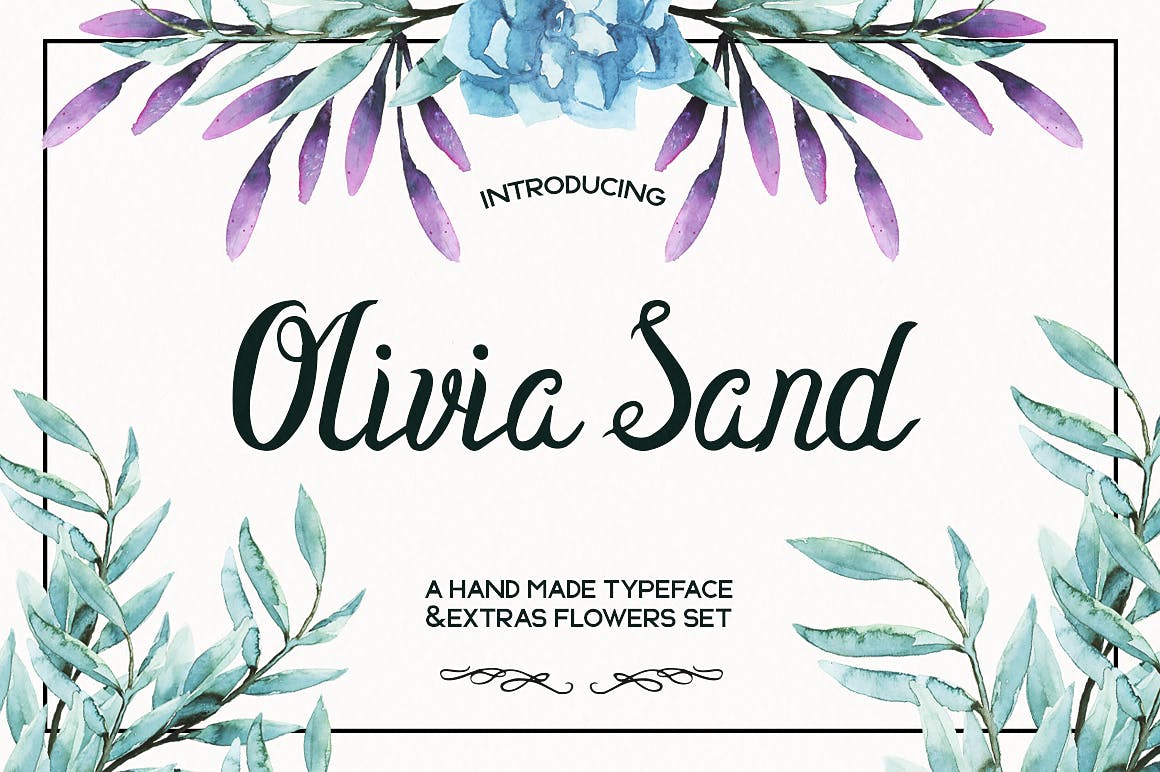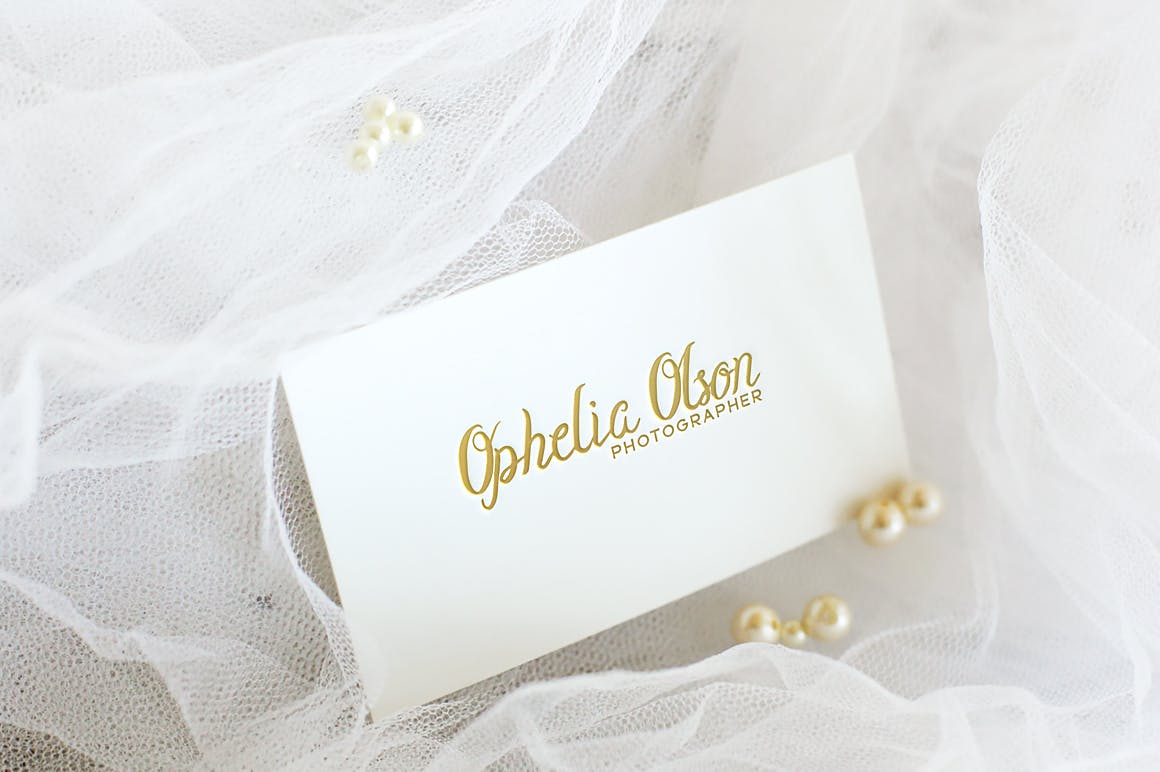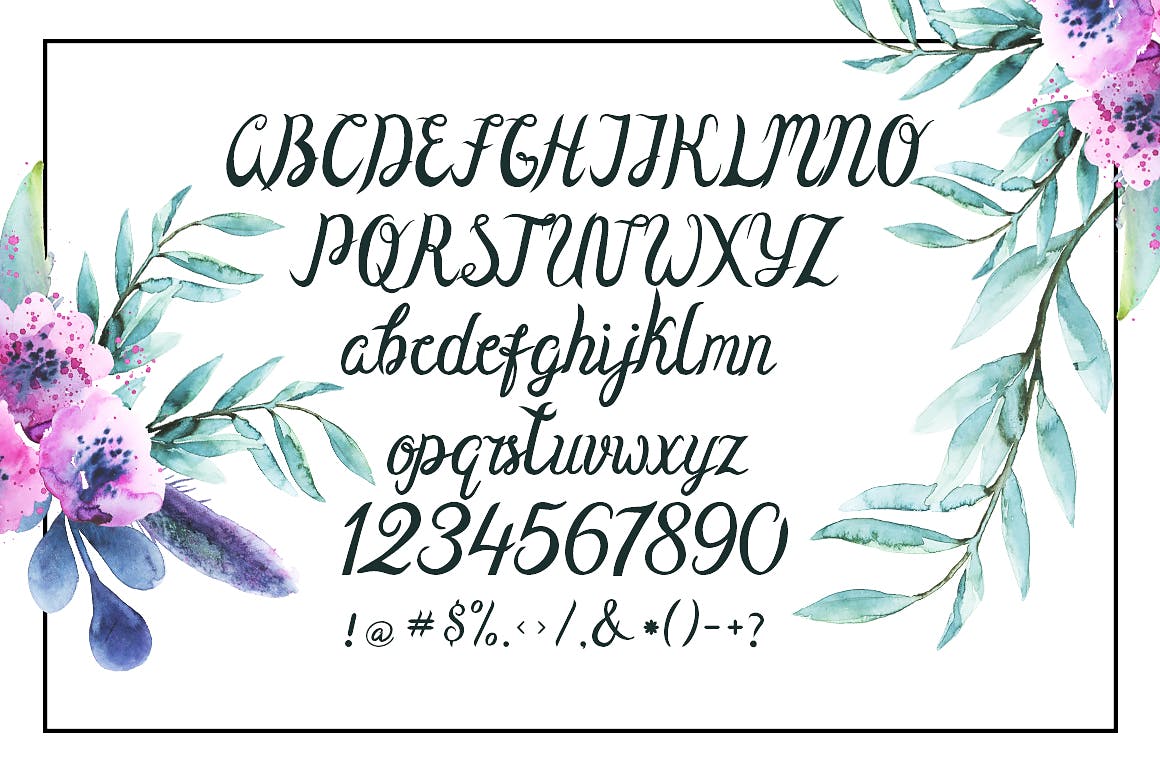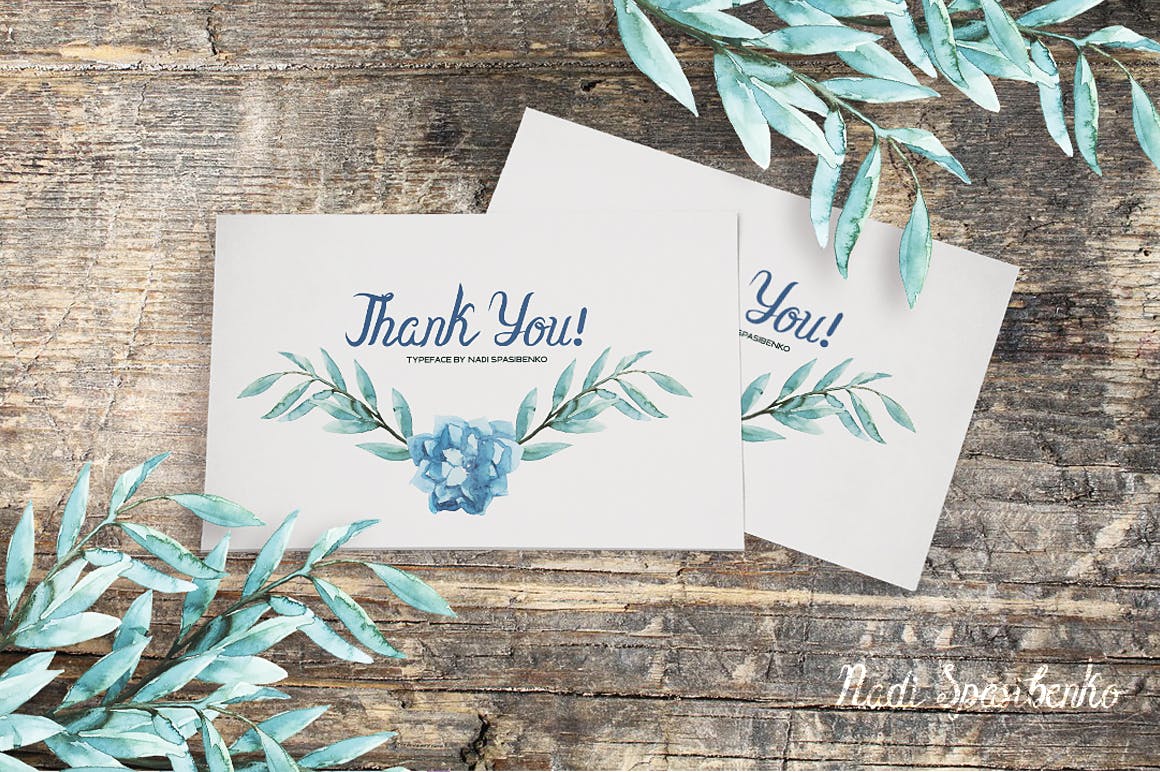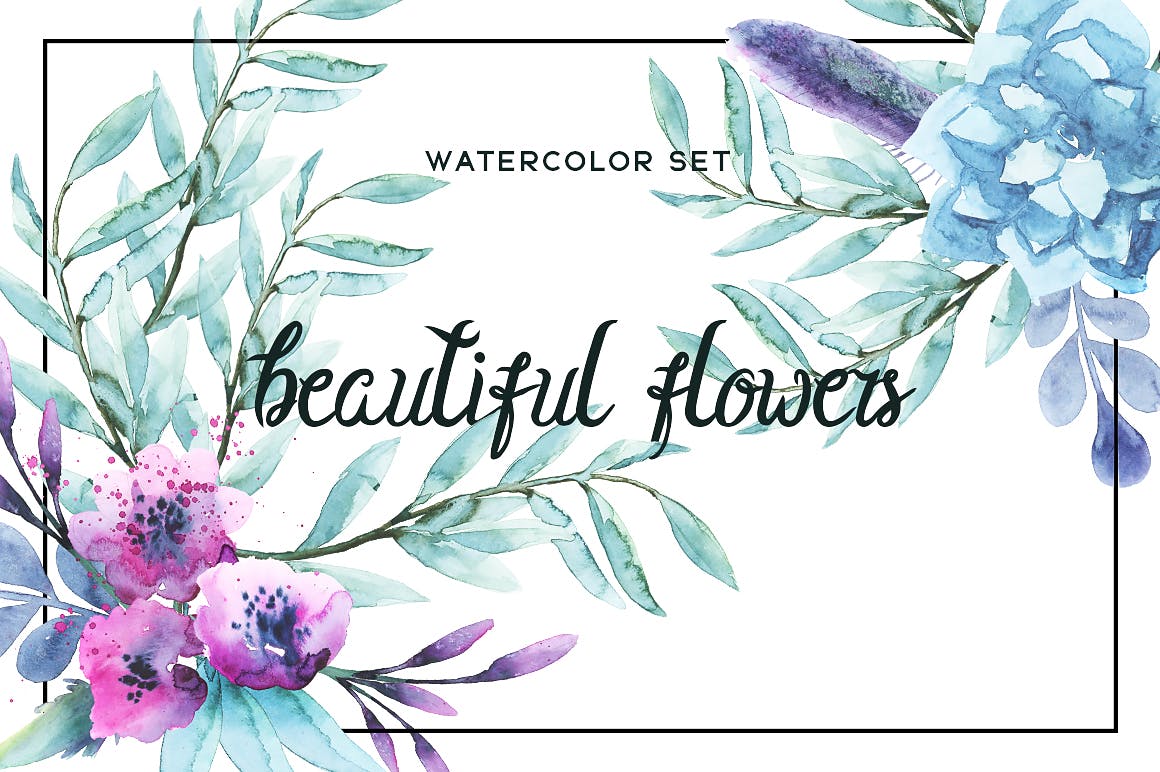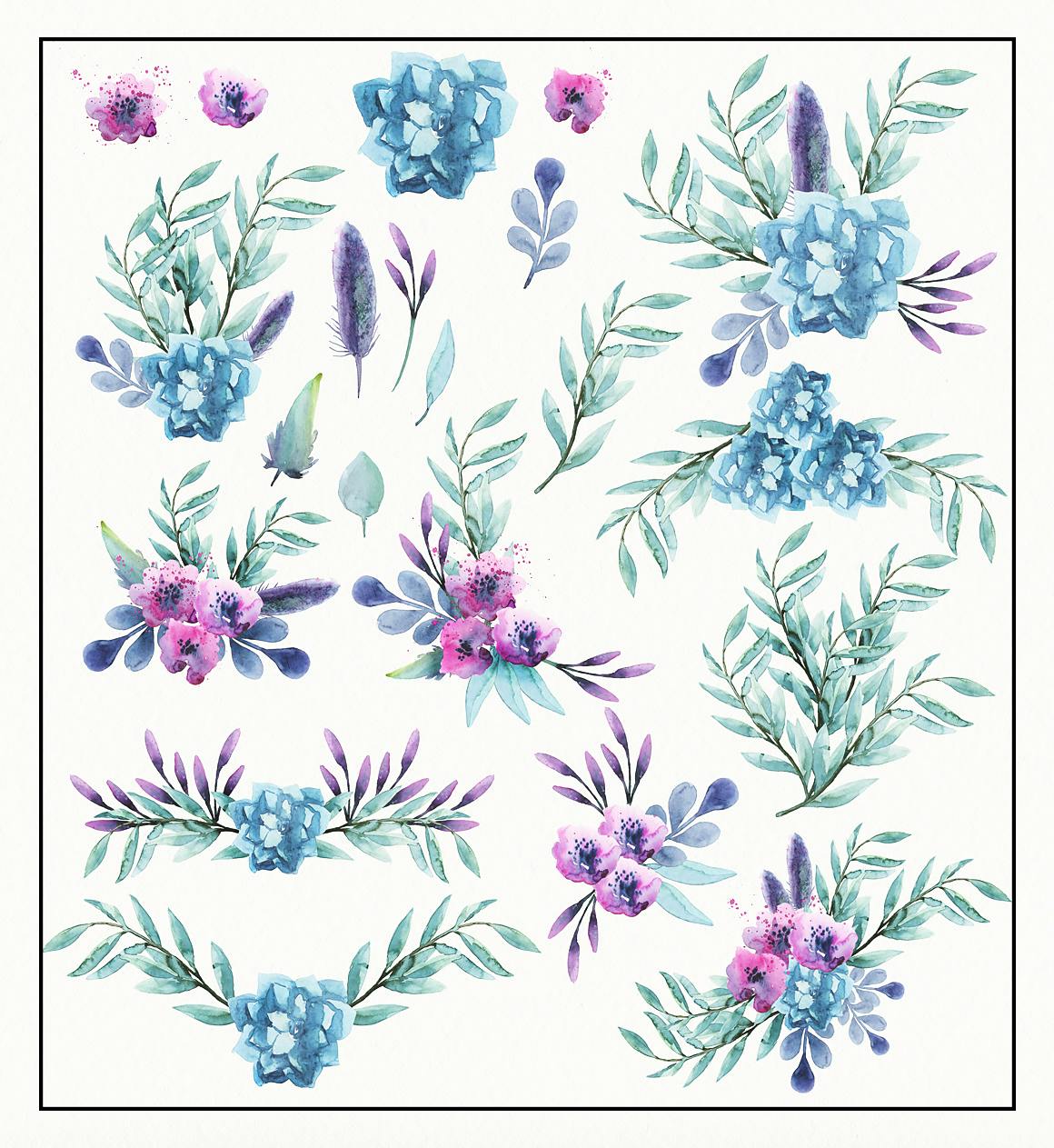
Olivia Sand Typeface Flowers set
مجموعه‌ای بی‌نظیر از گل‌های آبرنگی و فونت دستی Olivia Sand.
این بسته شامل ۲۱ فایل PNG با گل‌های زیبا و آبرنگی مناسب برای طراحی لوگو و دعوت‌نامه‌ها و همچنین یک فونت دست‌ساز از Nadi Spasibenko می‌باشد. تمامی تصاویر با کیفیت ۳۰۰ dpi ارائه شده‌اند.
مناسب برای:
• دعوت‌نامه‌ها
• ایستگاه‌های بسته‌بندی
• کارت‌های تبریک
• وب‌سایت‌ها
• و بسیاری دیگر...